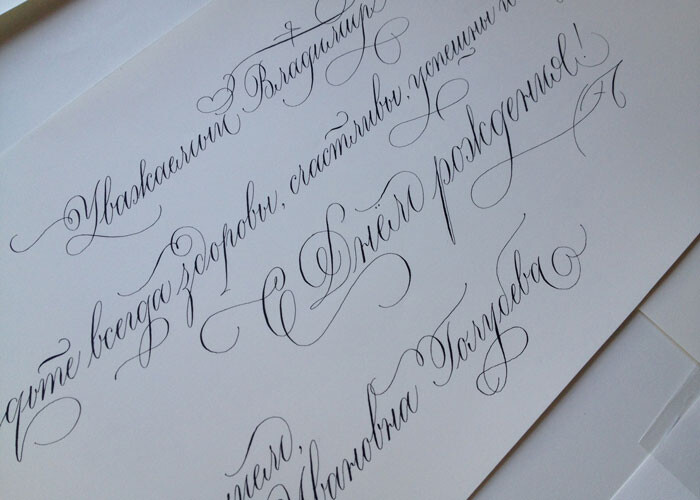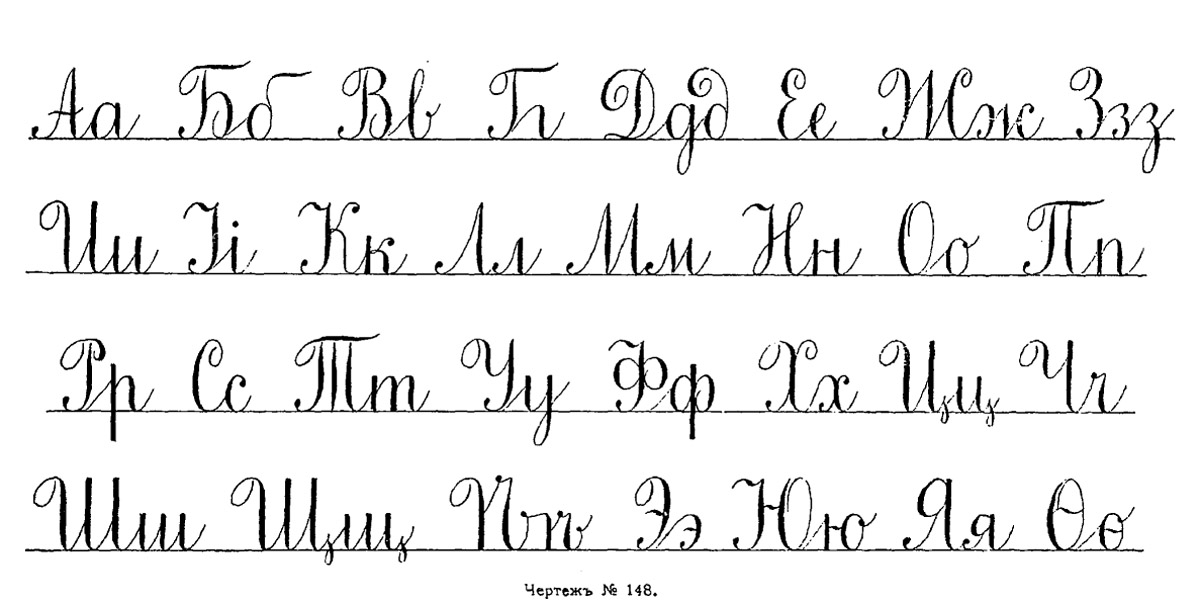
Каллиграфия. Рукописные шрифты Запада и Востока 112
Рим 9
Колонна Траяна 10
Римская капитель 58-71
Высеченные надписи 61
Конструкция букв 59—61
Проекты 62—67
Происхождение 58
Рондо, готический шрифт 92—93
Рунический шрифт 8
Как держать ручку 21, 156, 167
Перья 14—15
Упражнения на написание
штрихов 24
Самодельная книга на русском
языке 150-151
Санскрит 8
Свитки
Древнегреческий 138-139
Каролингский 54—55
Написанный римской
капителью 66—67
Символы 7
Системы письменности 7—9
Слоговые 7, 8
Стихотворение,
иллюминированное позолотой
148-149
Строки 25-27, 29, 73, 127, 167,
224
Табличка с кельтским именем
78-79
Таблички для рассаживания
гостей 120-121
Тань, китайская династия 183,
198
Тао, проект 190-191
Тарелка с арабской вязью
174-175
Типографские шрифты 10
Тростниковые перья 15, 157
Для арабской каллиграфии
165, 166
Для арабской каллиграфии
165
Для китайской каллиграфии
184
Углы наклона при письме 22
Унциальные шрифты 72—85
История 72
Конструкции букв 73
Полуунциальный шрифт
74-75
См.
также Кельтские шрифты
Упражнения с парными
карандашами 23—24
Финикийская письменность 8, 9,
125
Фломастеры с фетровым пером
15, 126
Футболка, украшенная
с помощью трафарета 70—71
Х-высота 25, 224
Хирагана, японский стиль
каллиграфии 198—199,
202-203
Х-линия 25, 29, 224
Цапф, Герман 11
Циновка для завтрака 206—207
на иврите 160-161
Цифры
Готические 92
Древнегреческие 133
Каролингские 38-39, 45
Курсивным шрифтом 104
Латинские 20
Полуунциальные 75
Рондо 92
«Часослов» герцога де Бери 11,
94-95
Шевити 162-163
Шекспир, сонет 106-107
Ширина пера 22
Экслибрис 108-109
Японская каллиграфия
Иностранные имена и
географические названия 205
История 198—199
Канджи, полукурсивный стиль
джиошо 201
Канджи, стандартный стиль
кайшо 198-199
Катакана 189—199, 204
Проекты 206-213
Соединение иероглифов 203
Хирагана 198-199, 202-203
Штрихи 200-201
Японские системы письменности
7,8,9
Фонемы кана 199
1
3
2,5
—
1.5
2.5
2
сз
2
1,5
С4
2.5
1.5
1,25
_
3
_
1
С5
3.5
1
0,75
_
4
0.5
0,6
_
5
_
0,5
С6
6
—
СЛОВАРЬ
Бочоночек.
Закругленная часть таких букв, как «о».
Верхний выносной элемент буквы. Самая верхняя часть таких
букв, как «1», выступающая над х-линией.
Верхняя линия. Самая верхняя линия строки. Эту линию
также называют линией прописных букв или линией
верхних выносных элементов букв. Эта линия отмечает
вершины прописных букв и верхних выносных элемен¬
тов строчных букв.
Засечка. Короткий декоративный штрих на конце буквы.
Линия прописных букв — см. Верхняя линия.
Направляющая линия. Общий термин, используемый для
описания различных карандашных линий, которыми
размечаются строки для каллиграфических надписей.
Нижний выносной элемент буквы. Самая нижняя часть таких
букв, как «j», уходящая под основную линию строки.
Нижняя линия. Самая нижняя линия строки. Эту линию на¬
зывают также линией нижних выносных элементов букв.
Основная линия строки. Линия строки, на которую опирает¬
ся основная часть (тело) буквы.
Перекладина. Горизонтальная линия в таких буквах, как «t».
Прописные буквы. Их называют также большими или за¬
главными.
Строка. Серия направляющих линий — как правило, от двух
до четырех — из которых состоит строка, расчерченная
для написания каллиграфических букв.
Строчные буквы. Эти буквы называют также маленькими.
Х-высота. Пространство между основной и х-линией строки.
Х-линия. Направляющая линия между основной и верхней
линией строки. По этой линии располагаются вершины
стандартных строчных букв, таких как «х».